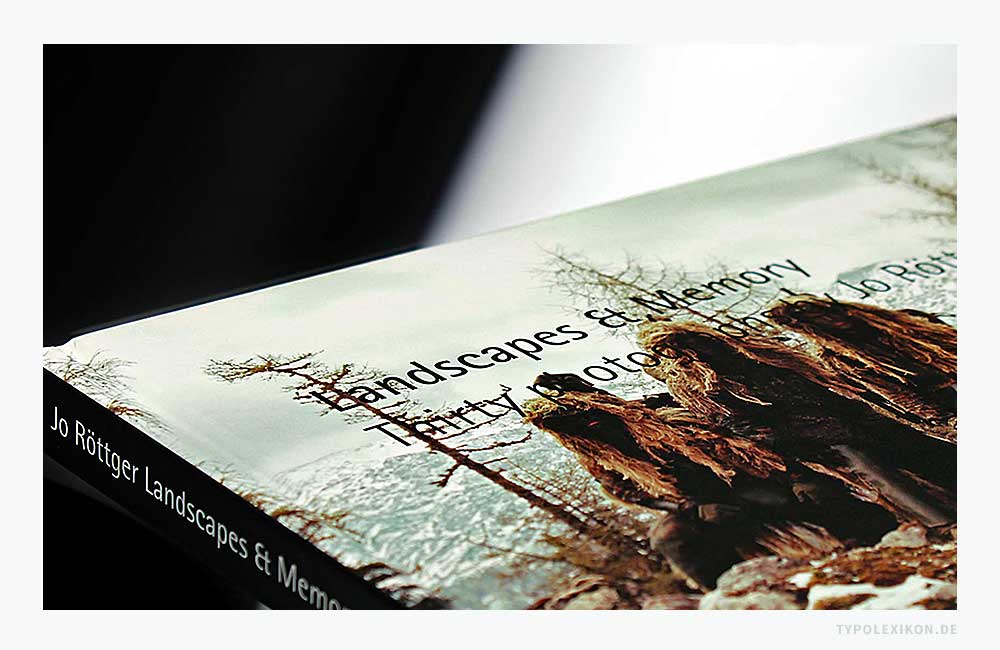
Buchrücken
Typografischer Terminus aus der Buchgestaltung, Buchherstellung und Druckweiterverarbeitung (Buchbinderei) für den Rücken eines Bucheinbandes, der sich zwischen Vorder- und Hinterdeckel eines Buches oder einer buchähnlichen Publikation befindet; Rückdeckel.
Bei gebundenen Büchern mit festem Umschlag (Hardcover) ist der Buchrücken jeweils mit einem »Gelenk« zwischen Vorderdeckel und Hinterdeckel verbunden, wobei der Buchblock von innen am Bundsteg eingehängt, also auf dem inneren Buchrücken zwischen vorderen und hinteren »Spiegel« befestigt wird. Der Buchrücken hält durch eine Buchleimung oder Buchbindung den Buchblock und somit die Seiten eines Buches.
Vorderdeckel, Buchrücken (Rückdeckel) und Hinterdeckel ergeben zusammen den Buchdeckel, 1) der bei gebundenen Büchern etwas über den Buchblock (Innenseiten) hinausragt. 2)
Der Buchrücken wird in der Regel mit einem Rückentitel beschriftet, welcher sich im Zuge der Prosperität der Typografie mit Beginn des 16. Jahrhunderts in Europa etabliert hat – explizit seit Bücher in Kloster-, Palast- und in Handbibliotheken in Regalen mit dem Rücken nach vorne aufbewahrt wurden.
Die Illustration zeigt ein geschlossenes Buch mit einem runden Buchrücken, der mit zwei Gelenken den Vorderdeckel und Rückdeckel eines Buches oder einer buchähnlichen Publikation verbindet.
Bis ins 20. Jahrhundert wurden runde und gerade Buchrücken mehrheitlich aufwendig gestaltet und verziert, beispielsweise mit Goldprägungen, Silberprägungen, Farbprägungen und Farblosprägungen bzw. Blindprägungen, handverzierten Ornamenten oder kostbaren Rückenvignetten. Mit Aufkommen des Schutzumschlages (Buchumschlag) Mitte des 19. Jahrhunderts hat sich diese Tradition im Wesentlichen peu à peu verflüchtigt.
Die Buchrücken eines Verlagsprogramms werden heute gerne im Sinne des Corporate Designs ganzheitlich gestaltet, beispielsweise die Jubiläumskassetten der »Insel-Bücherei« oder die von dem Grafiker Willy Fleckhaus (1925-1983) gestalteten »Regenbogen-Taschenbücher« des Suhrkamp Verlages.
Rückentitel
Auf dem Buchrücken befindet sich der Rückentitel. Hier werden Autor, Titel eines Buches und Verlag – z.B. in Form eines Signets – genannt. Es gibt drei unterschiedliche Beschriftungen bei Rückentiteln:
• Waagrechter Quertitel
Waagrecht mit und ohne Rückenschild (Rückenvignette). Bei einem im Regal aufrecht stehenden Buch kann man den Kopf gerade halten, um den Rückentitel eines Buches lesen zu können. Dies ist in der Regel nur bei seitenstarken Publikationen möglich.
• Linksdrehender Längstitel
Linksdrehend von Fuss zu Kopf. Bei einem im Regal aufrecht stehenden Buch muss man den Kopf nach links neigen, um den Rückentitel eines Buches von unten nach oben lesen zu können.
• Rechtsdrehender Längstitel
Rechtsdrehend von Kopf zu Fuss. Bei einem im Regal aufrecht stehenden Buch muss man den Kopf nach rechts neigen, um den Rückentitel eines stehenden Buches von oben nach unten lesen zu können.
Die Begriffe »linksdrehend« und »rechtsdrehend« beziehen sich dabei immer auf die jeweilige Neigung des Kopfes – aus der Sicht des Lesers – beim Lesen eines Buchrückens eines Buches, das aufrecht in einem Regal steht. Bei Schriftsystemen mit rechtsbündiger Satzausrichtung, z.B. im Arabischen oder im Hebräischen, verhält es sich natürlich andersherum.
Die Beschriftung eines Buchrückens wird als Rücktitel bezeichnet. Gebräuchlich sind drei Varianten: der waagrechte Quertitel, der linksdrehende Längstitel und der rechtsdrehende Längstitel.
Eine verbindliche Norm für die Laufrichtung auf einem Buchrücken existiert in Deutschland, Österreich und der Schweiz nicht. 3) Im deutschsprachigen Raum werden Rückentitel unterschiedlich, international bei Schriften römischen Ursprungs (Latin/Roman) meist überwiegend rechtsdrehend gesetzt.
Vorteil eines rechtsdrehenden Längstitel
Bei großformatigen Büchern, also bei Tischbüchern, 4)  z.B. bei Fotobüchern, Magazinen oder Geschäftsberichten, die oft auch im Bücherregal oder auf Tischen mit dem Vorderdeckel (Titelseite/U1) nach oben liegen, ist es immer vorteilhaft, rechtsdrehende Buchrücken zu verwenden, da ein Rezipient sowohl den Vorderdeckel bzw. die Titelseite als auch den Buchrücken lesen kann, was bei einem linksdrehenden Buchrücken nicht möglich ist. Die Lesbarkeit eines rechtsdrehenden Buchrückens ist statistisch betrachtet somit immer größer und ästhetisch ausgewogener. 5)
Der Vorteil eines rechtsdrehenden Längstitel ist die bessere Lesbarkeit des Rücktites, sobald ein Buch oder eine buchähnliche Publikation, z.B. ein Geschäftsbericht, ein Katalog oder ein Magazin, im Regal oder auf einem Tisch liegt. © Bildzitat: Fotoband »Landscapes & Memory« von Jo Röttger, erschienen bei peperoni books.
↑1 Anmerkung: Beim einem Softcover, z.B. einem Taschenbuch, wird der Buchdeckel in der Regel in dspr. Verlagen als »Umschlag« bezeichnet.
↑2 Tipp: Erfahrungsgemäß sollte bei gebundenen Handbüchern der Buchdeckel nicht mehr als 2 mm über den Buchblock hinausragen.
↑4 Anmerkung: Man unterscheidet in Bezug auf Größe und Gewicht zwischen Hand- und Tischbüchern.
↑5 Tipp: Im Sinne eines Corporate Designs oder eines Seriencharakters ist es immer empfehlenswert, dass alle Rückentitel der Publikationen eines Verlages oder einer Firma die gleiche Laufrichtung aufweisen.